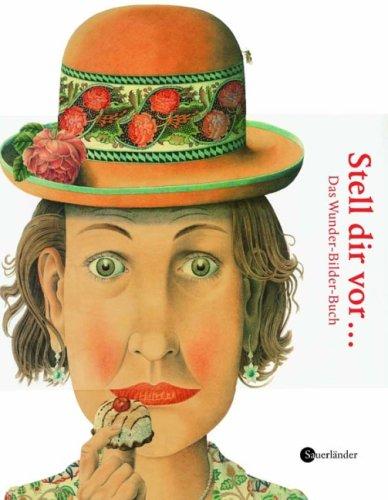
Scharfer Blick gefragt
Hallo, ist auf diesem Buchtitel vor den drei Punkten ein Leerraum (egal was für einer)? Ich frage nicht, ob einer hingehört – das ist mir selber klar –, sondern ob dort einer da ist. Es geht darum, den Titel im Original zu zitieren. Auf der amazon-Beschreibungsseite steht er so: „Stell dir vor. Das Wunder-Bilder-Buch“ :?
Nachdem das Wort "vor" gekernt aussieht (das o ist näher am v), würde ich erwarten, daß auch die Punkte näher am bzw. unter dem r wären, wenn kein Leerzeichen dazwischen wäre.
Wenn ich alle Verneinungen zusammenrechne, komme ich auf: es ist einer drin :D ok, danke!